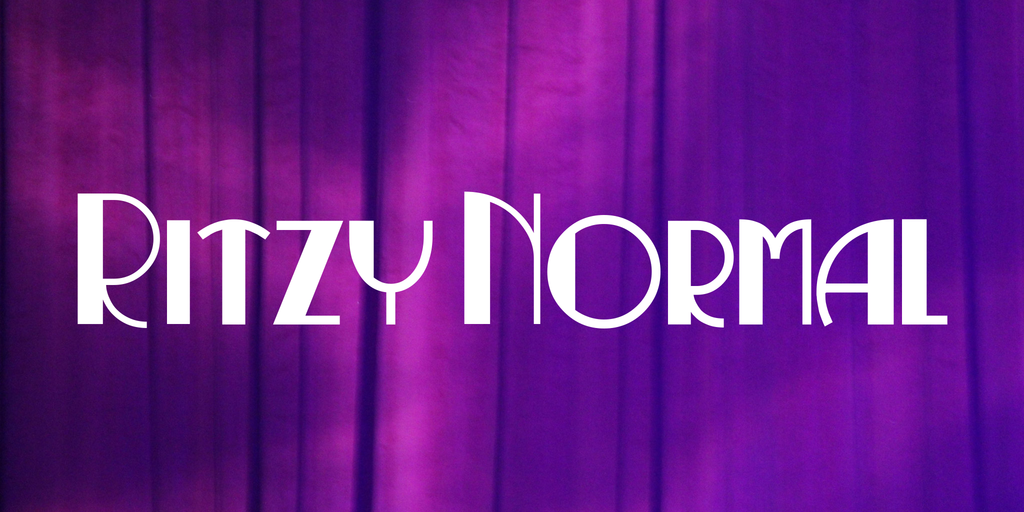
Ritzy Normal Font
A fonte Ritzy Normal é uma releitura moderna e decoração cuidadosamente definida do icônico Busorama dos anos 60. Inspirada no gosto retro, esta fonte redefiniu seus traços para um estilo atemporal que combina elementos de desenho artístico com uma tipografia sóbria. Ideal para os projetos digitais e impressos que procuram um toque nostálgico sem perder a elegância, Ritzy Normal é perfeito para criações que valorizam o bom gosto e a simplicidade. Para designers e criadores de conteúdo que buscam uma fonte que não só se destaca, mas também traz à tona memórias dos anos 60 ao mesmo tempo em que oferece um visual contemporâneo, Ritzy Normal é uma excelente escolha para qualquer projeto retro ou moderno. Com traços estreitos e grossos harmoniosamente distribuídos, esta fonte atingiu o equilíbrio perfeito entre sofisticação e simplicidade.